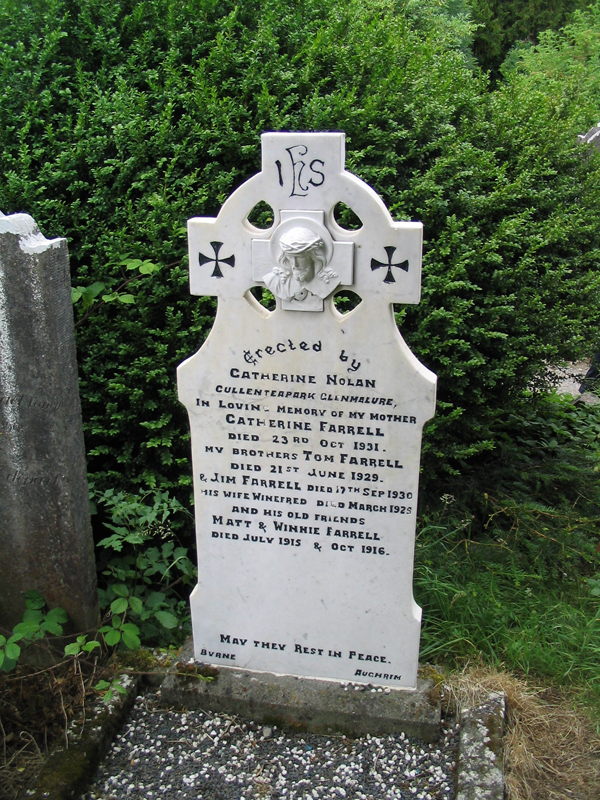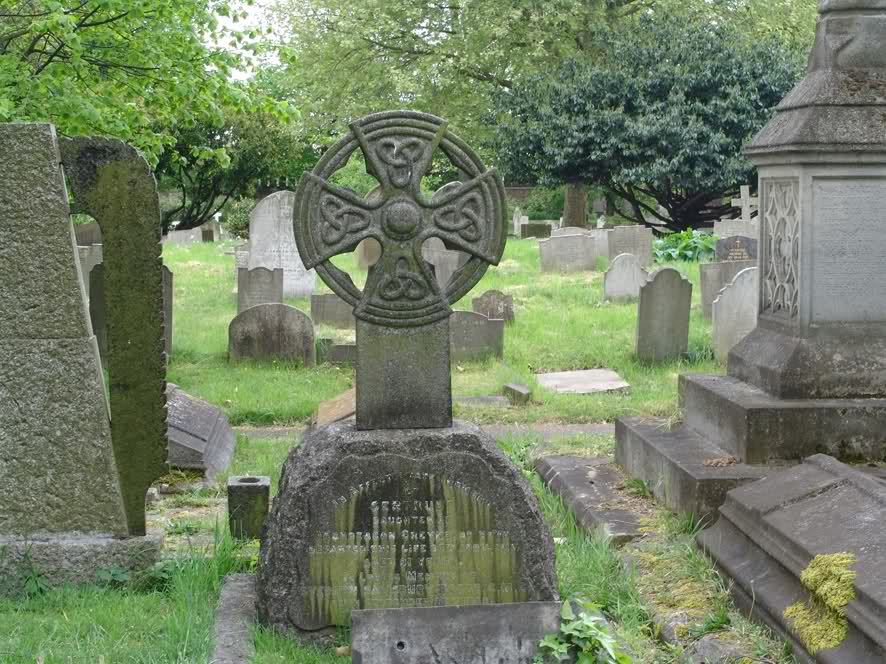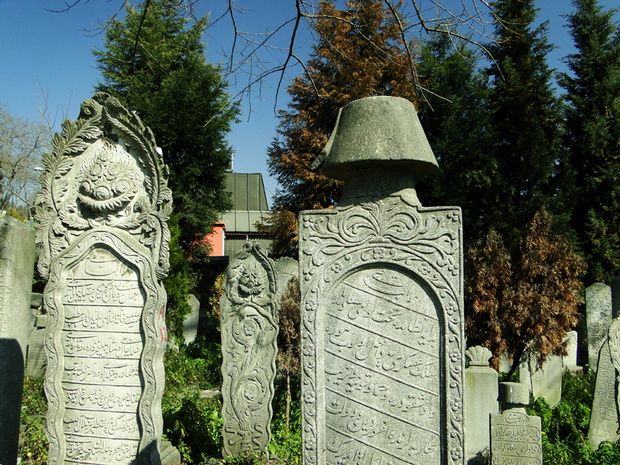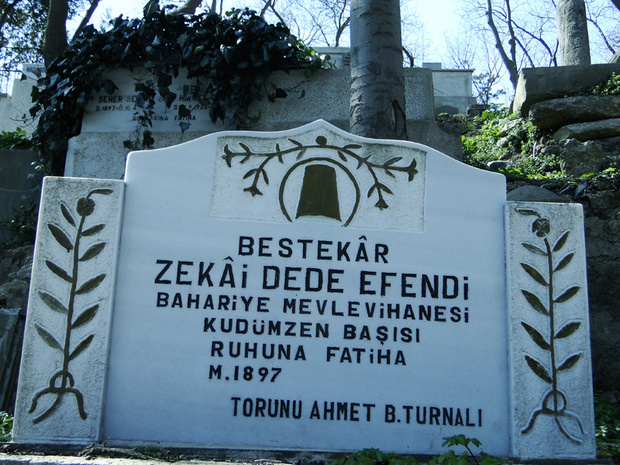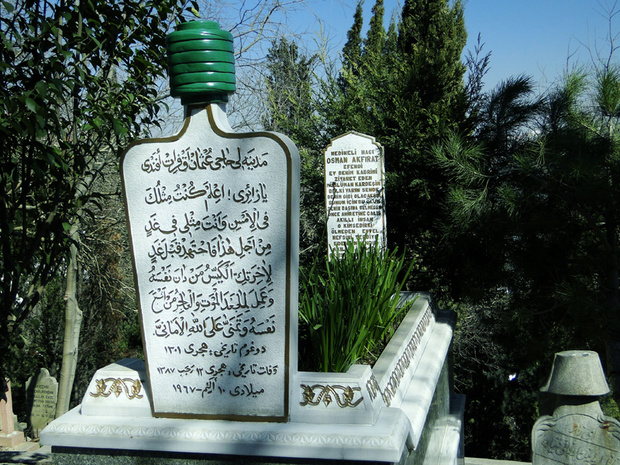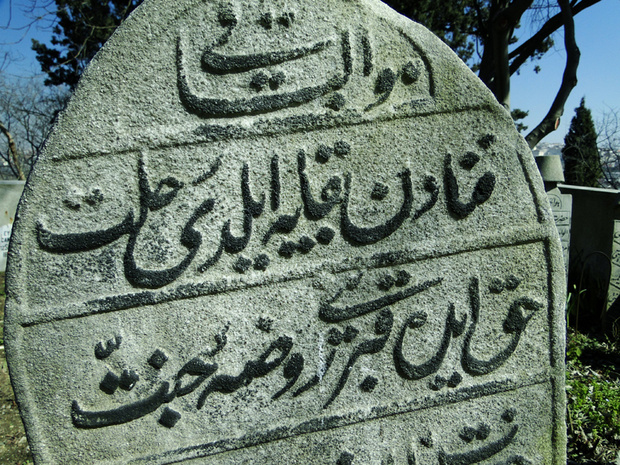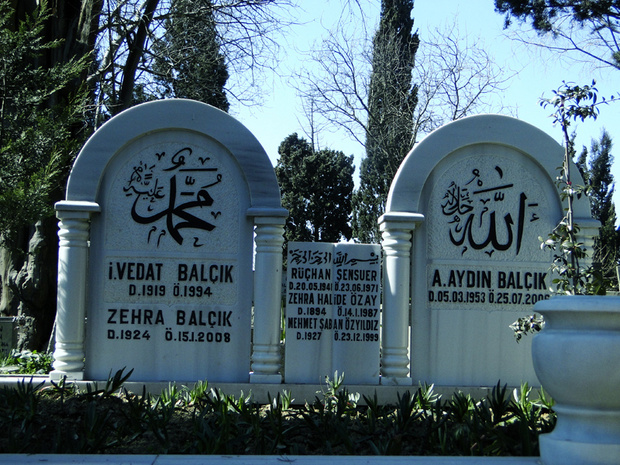
ist hier im Forum kein Steinmetz oder Bildhauer zugegen?
Erwin Krump fällt mir da spontan ein.
Nachdem ich im Zusammenhang mit dem Thema Grabsteine im Forum genannt wurde, möchte ich meine persönliche Sicht, weniger als Typograf sondern als Bildhauer, auf dieses Thema darstellen.
Grabplatten, Beschriftung etc. fallen in den Arbeitsbereich des Steinmetzes und sind fast zu 100 Prozent Maschinenarbeit.
Meine eigene bildhauerische Arbeit beschränkt sich auf Skulpturen.
Auf mich wirkt in erster Linie der Gesamteindruck (s. Abbildungen), den ein Friedhof auf mich hinterläßt, weniger der einzelne Grabstein. Als Typograf muss mir auch klar sein, dass Grabinschriften keine Buchtitel oder sonstige Druckerzeugnisse sind, auch wenn der einzelne Stein eine gute optische Wirkung ergeben würde.
Zu den Abbildungen:
Bild 1 – Von mir gefertigte Skulptur anstelle eines Grabsteines. Die Steinplatte mit Namen (nicht im Bild) wurde davor horizontal montiert.
Bild 2 und 3 – Friedhof Brompton in London. Nicht jeder Stein steht für sich, sondern die Steine zusammen ergeben ein Ganzes. Interessant das Zusammenspiel mit der Natur.
Grabplatten, Beschriftung etc. fallen in den Arbeitsbereich des Steinmetzes und sind fast zu 100 Prozent Maschinenarbeit.
heißt das also, dass
a) der steinmetz seine eigenen schriften hat und damit mittels fräse graviert oder
b) er auch sowas wie bezierkurven weiterverarbeiten kann.
weil ich das eben auch schon mal hatte: kann der mit unseren daten weiterarbeiten, oder druckt sich der mein pdf aus und bastelt das dann mehr schlecht als recht nach?
Also, ich habe bei meinen Grabsteinprojekten offene Vektordaten geliefert und die Steinmetze haben sie weiterverarbeitet.
Grundsätzlich haben die Steinmetze aber auch eigenen Schriften, die man sich aus einem Katalog aussuchen kann. Meist sind das Schriften, die die nötige Stabilität mitbringen, damit sie sich gut in Stein umsetzen lassen.
Die von mir gewählte Berkeley OldStyle musste ich damals noch gezielt modifizieren, da die Serifen in der gewählten Schriftgröße zu fein gewesen wären.
Hast Du davon noch ein Bild (vorher/nachher)?
Bestimmt nicht maschinengefräst:
Glendalaugh, Irland, 2005
Friedhof Brompton in London. Nicht jeder Stein steht für sich, sondern die Steine zusammen ergeben ein Ganzes. Interessant das Zusammenspiel mit der Natur.
Schön. Das erinnert mich an einen Kleinstadtfriedhof, dessen alter Teil komplett von Efeu überwuchert ist. Es gibt dort keine Wege mehr, man läuft auf einem Efeuteppich, und das Efeu rankt sich auch um die Baumstämme. Höhere Grabsteine ragen aus dem Efeuteppich heraus, flachere sind gar nicht oder nur durch einen Efeuhuckel zu erkennen. Wenn das kein Bezug zur Natur (die sich halt irgendwann alles wiederholt) ist!
Leider habe ich im Moment kein Foto von der Gesamtansicht (ich werde das nächste Mal, wenn ich in der Gegend bin, eins machen). Hier ist ein einzelnes Grab:
(Früher stand auf dem Stein noch ein Marmor-Engel, der aber schon vor Jahrzehnten geklaut wurde.)
Weiß irgendjemand was zu den verwendeten Schriften?
Neben einigen interessanten Buchstaben formen (gebrochenes S; A, J und r der Serifenlosen) fand ich es noch ganz spannend, wie der gesamte Text auf dem Stein konsequent als Satz behandelt und entsprechend mit Interpunktion versehen wurde, incl. des Nachnamens.
Die von mir gewählte Berkeley OldStyle musste ich damals noch gezielt modifizieren, da die Serifen in der gewählten Schriftgröße zu fein gewesen wären.
Hast Du davon noch ein Bild (vorher/nachher)?
Ich habe nachgeschaut, leider liegt die entsprechende Platte bei mir zu Hause und ich bin gerade auf Reisen. Nächste Woche kann ich den Vergleich nachliefern. :)
Nix so besonderes, aber ich mag's mal trotzdem zeigen:
Das Grab Kurt Tucholskys in Mariefred, Schweden.
Er liegt dort begraben, weil es der Ort ist, in dem seine Liebesgeschichte "Schloss Gripsholm" spielt und weil er politisch motiviert eh nicht mehr in Deutschland lebte (gelebt hat er allerdings in Göteborg).
Das Zitat aus Goetes Faust II wurde erst nachträglich angebracht. Tucholsky selbst hatte mal "Hier ruht ein goldenes Herz und eine eiserne Schnauez - Gute Nacht!" (für sein Pseudonym allerdings) vorgeschlagen.
grabsteine auf dem 'piratenfriedhof' borkum, das sind allerdings replikas. die originale stehen im heimatmuseum:
:tutor: HUŸS · VROUW heisst übrigens hausfrau